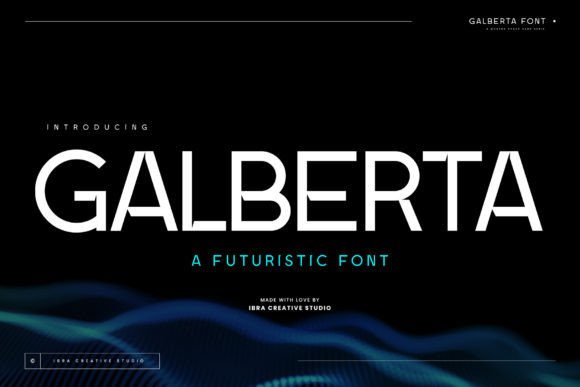
Galberta
Encontrar os elementos de design certos pode ser um desafio, mas Galberta oferece uma coleção excepcional que eleva o seu trabalho instantaneamente.